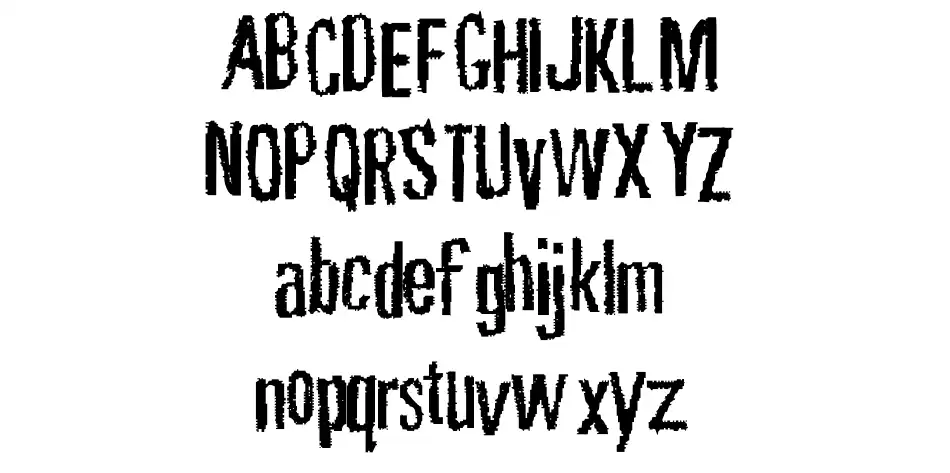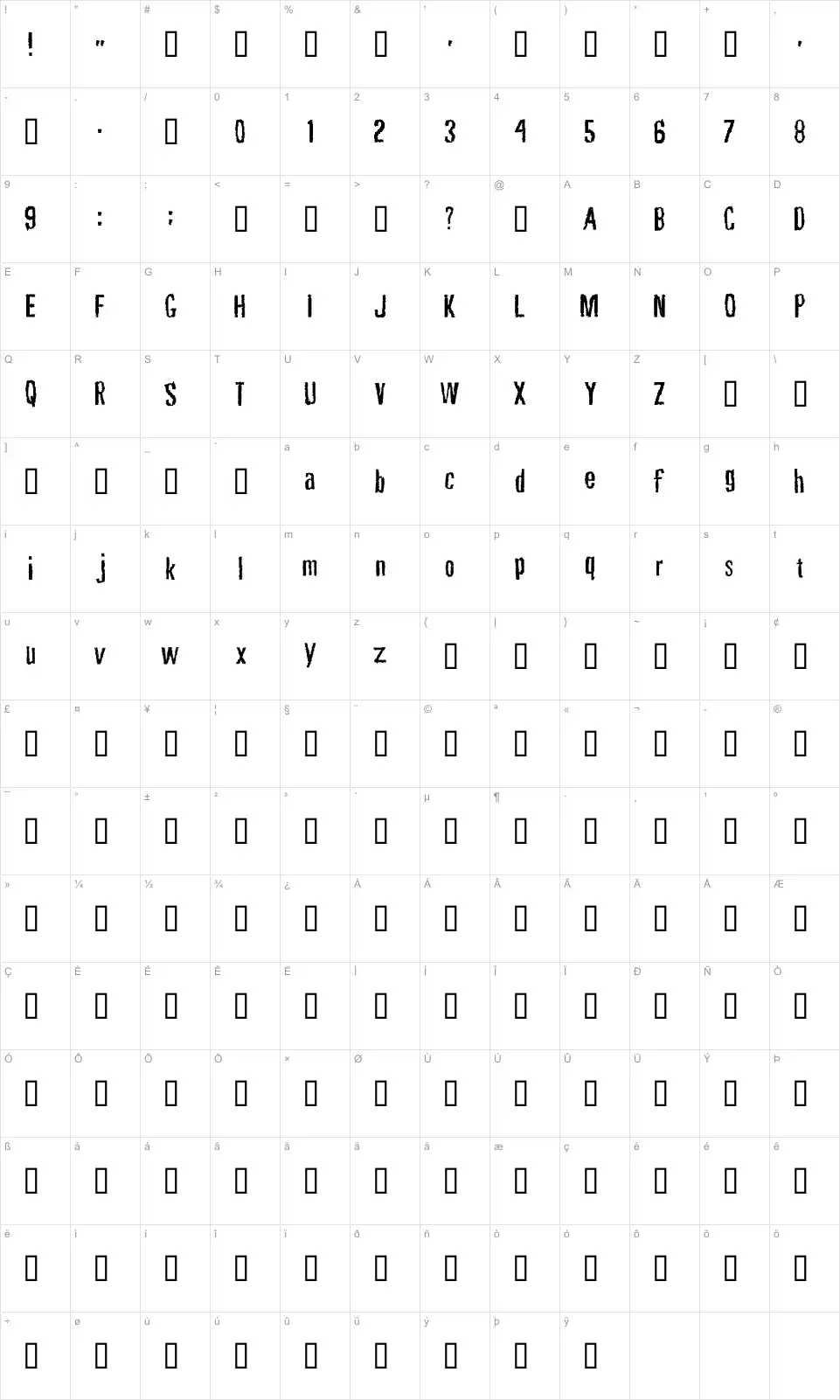
Rubbing Font – Download Grátis
A Rubbing Font é uma fonte Fancy criada pelo Glyphobet Font Foundry, disponível de graça e em formato TTF. Esta fonte é perfeitamente adequada para criar um estilo único e chamativo em seus projetos digitais, especialmente em contextos que exigem um efeito de destroçamento. Se você está procurando por uma maneira interessante de dar uma capa especial a seu texto, a Rubbing Font pode ser a solução perfeita. Para ter uma idéia do que ela pode fazer, você pode baixar a fonte ou gerar uma prévia personalizada de texto online antes de começar a usá-la. Com uma categoria de “Destroy”, a Rubbing Font destaca-se como uma maneira criativa de transformar seu conteúdo em algo realmente chamativo. A fonte foi adicionada ao banco de dados em 12 de julho de 2022 e tem sido baixada por mais de 1400 pessoas. Para mais informações, visite o site do designer, disponível no endereço https://glyphobet.net/typography.